網(wǎng)頁設(shè)計世界不斷發(fā)展。每年,一些趨勢誕生,一些褪色,一些只是繼續(xù)繁榮。很像像素是一個圖像,這些設(shè)計元素匯集在一起,創(chuàng)造了互聯(lián)網(wǎng)的臉,因為我們知道。
我們在屏幕上看到的圖形演變往往是巨大的科技和網(wǎng)絡(luò)公司創(chuàng)新的結(jié)果,這并不是秘密。但是設(shè)計也受到時尚,新聞現(xiàn)象,文化活動等多種時間敏感要素的影響。
所以百萬美元的問題是:今年熱的設(shè)計趨勢是什么?我們很高興你問!如你所知,維克斯提供了 令人驚嘆的網(wǎng)站模板 ,以幫助你開始你的網(wǎng)站上右腳。但我們進(jìn)一步。我們采訪了創(chuàng)建我們的模板的設(shè)計師,并挑選了他們的大腦的所有信息,在2017年將需要的設(shè)計趨勢,以及如何使用它們來保持您的網(wǎng)站看起來新鮮。
一般忽略:前后流行趨勢
在這個移動時代,我們尋找的一切都在我們的指尖 - 從字面上,我們只需要滾動,以找到它。即使在桌面上,我們沉迷于我們的鼠標(biāo)滾輪或觸控板,這主要是感謝社交網(wǎng)絡(luò)。隨著網(wǎng)站越來越長(見長滾動),圖像去海岸到海岸和排版的規(guī)則正在改變,以滿足這些新布局的需要。
總而言之,網(wǎng)站所有者不再專注于向訪問者提供詳細(xì)的信息,而是選擇以高效和即時的方式傳達(dá)他們的信息。不要誤解我們:所有的內(nèi)容仍然存在,它只是以更簡潔和“性感”的方式顯示。
只是為了給你一個例子,這里是我們的顧問模板在過去2年中的演變。
現(xiàn)在,你已經(jīng)有了這個想法,讓我們看看下一年流行的風(fēng)格:
使用GIF吸引注意
好吧。讓我們清楚。濫用Gif和動畫肯定會傷害您的網(wǎng)站的UX(用戶體驗)。但是以正確的方式做,你可以通過強(qiáng)調(diào)重要的方面,使你的網(wǎng)站生活,終將您的設(shè)計到一個新的水平,而不讓你的訪客瞇。
GIF格式(和動畫),顯示出設(shè)計的深刻理解,并給予一個復(fù)雜的觸摸到任何網(wǎng)站。我們建議您使用這些特定的元素,你想要脫穎而出,如銷售彈出窗口,暢銷的產(chǎn)品等。如果你真的想在網(wǎng)絡(luò)上酷的孩子,添加一些深入到您的站點的視差效果。 提示:T已他的人在維克斯編輯器中是驚人的,并在那里等著你。
除了Gifs /動畫的運動,你可以創(chuàng)建一個3D效果,將繼續(xù)以一個迷人的方式告訴你的整個故事。如果你找到符合你需要的食譜,你可以確保你的訪客的嘴會澆水。需要一個櫻桃在上面?看看這些免費 cinemagraphs!
想想在盒子外有3D幾何形狀
現(xiàn)在有一點歷史。曾幾何時,大數(shù)字趨勢skeuomorphism -保佑我們。這個想法是在數(shù)字接口上模仿現(xiàn)實生活中的物體。例如,你可能記得iPhone上的記事本看起來像一個實際的記事本。雖然很酷和清晰,它感覺不夠現(xiàn)代。然后,扁平設(shè)計 了通過網(wǎng)絡(luò)(微軟Windows 8風(fēng)格)簡約的圖標(biāo)并沒有提到我們的實際世界的強(qiáng)烈的色塊任何它開始處處流露出了。雖然創(chuàng)新,人們得到了一個有點失落。后,谷歌推出了材料設(shè)計和帶來了一些新鮮的視角幾何形狀,增加了一些陰影,運動和大膽的幾何風(fēng)格。
為什么我們告訴你這個故事?因為當(dāng)Google翻動翼時,整個網(wǎng)絡(luò)都會動搖。如果他們使用幾何形狀,我們應(yīng)該。視覺上,準(zhǔn)備看到越來越多的3D幾何形狀的網(wǎng)站背景和設(shè)計支持一般。為什么?因為Google(除了你的媽媽)知道好。
用華麗的排版打破規(guī)則
是。大的排版已經(jīng)趨向于很長時間了,這就是為什么越來越多的網(wǎng)頁設(shè)計師試圖展示他們的創(chuàng)造力和潛水到未知的水域。 在排版規(guī)則非常嚴(yán)格,像連字的單詞和不清楚的線條之類的東西是禁忌。但是 - 不再。
當(dāng)然,掌握排版是一門藝術(shù),畢加索說:“學(xué)習(xí)規(guī)則像一個職業(yè),所以你可以打破他們作為一個藝術(shù)家!睋Q句話說,你應(yīng)該調(diào)查的主題,盡可能多的處理之前設(shè)計工具。一旦你對自己的知識充滿信心,開始使用顏色,排列間距,將它與圖像結(jié)合,混合不同的字體...天空的極限。
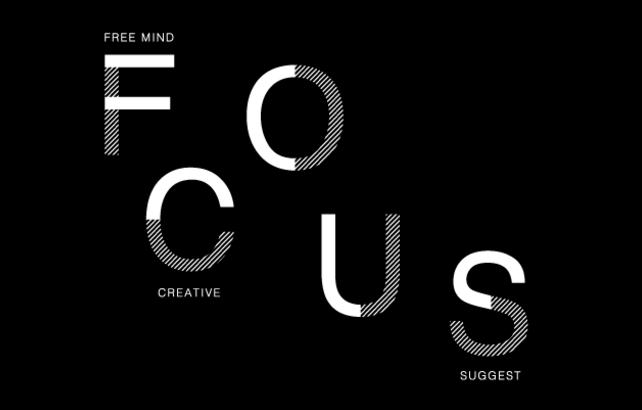
前衛(wèi):成為流行音樂之王(藝術(shù))
如果你對藝術(shù)趨勢有敏銳的洞察力,你可能注意到越來越多的流行色彩在網(wǎng)絡(luò)上流行。原因:前衛(wèi)藝術(shù)回來了大時間!這說明這并不意味著每個人都應(yīng)該跳上趨勢。根據(jù)你的業(yè)務(wù)的性質(zhì)和視覺識別,你可能決定使用或不使用。但這絕對是一個有趣和有趣的趨勢知道。和往常一樣,如果你是Wix用戶,你不必是安迪·沃霍爾在你的網(wǎng)站上使用這種風(fēng)格的圖像。只需選擇你想從我們好的那些免費圖片庫。多么酷?
流行
獎金提示!自定義您的Google地圖
現(xiàn)在,每個在線消費者習(xí)慣用紅色的針看到著名的地圖。問題:大多數(shù)網(wǎng)站的地圖看起來完全一樣。是時候改變了。一個酷和時尚的設(shè)計提示是以一種補(bǔ)充您的設(shè)計的方式定制您的地圖。與WiX的,你可以個性化您的谷歌地圖,以確保你站在客戶的心中。顯然,你不必為此支付一分錢。它在房子!